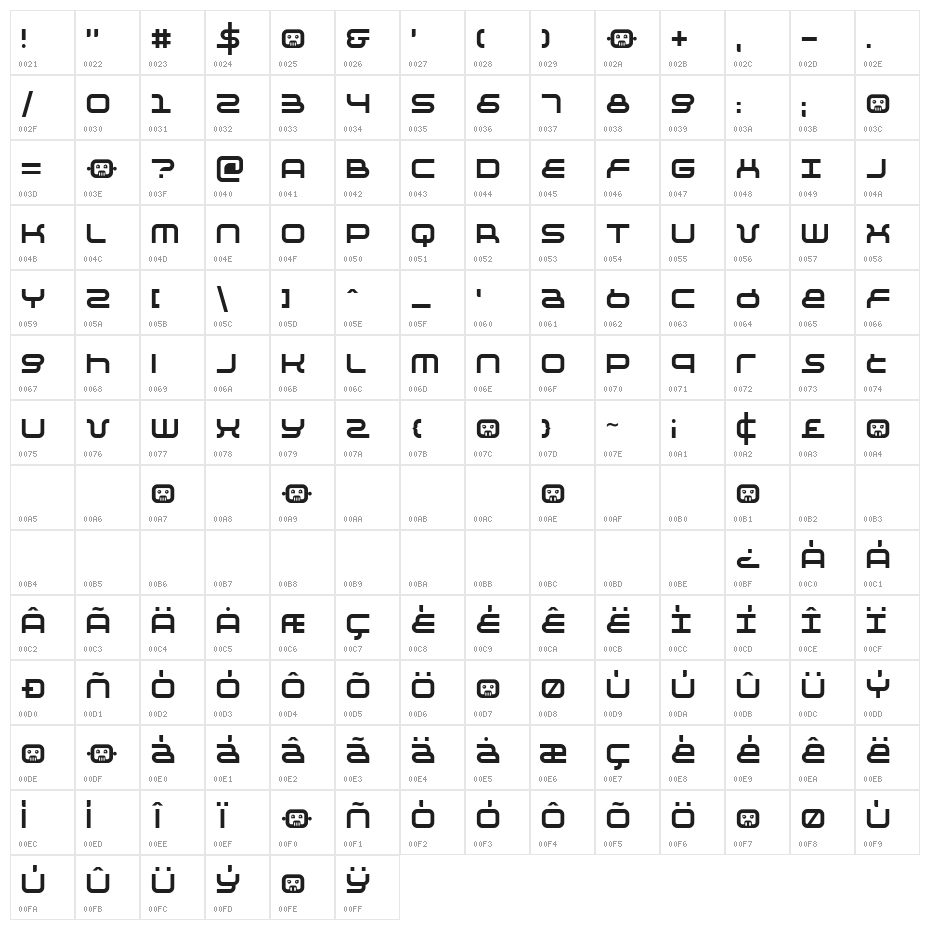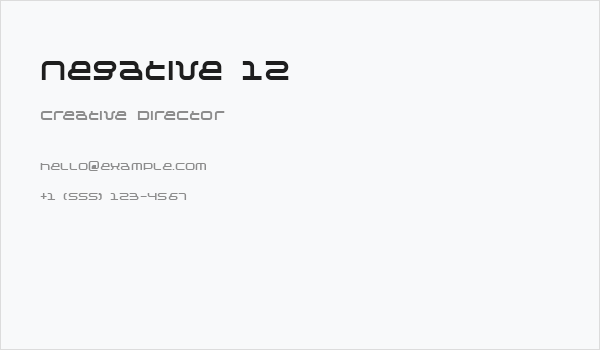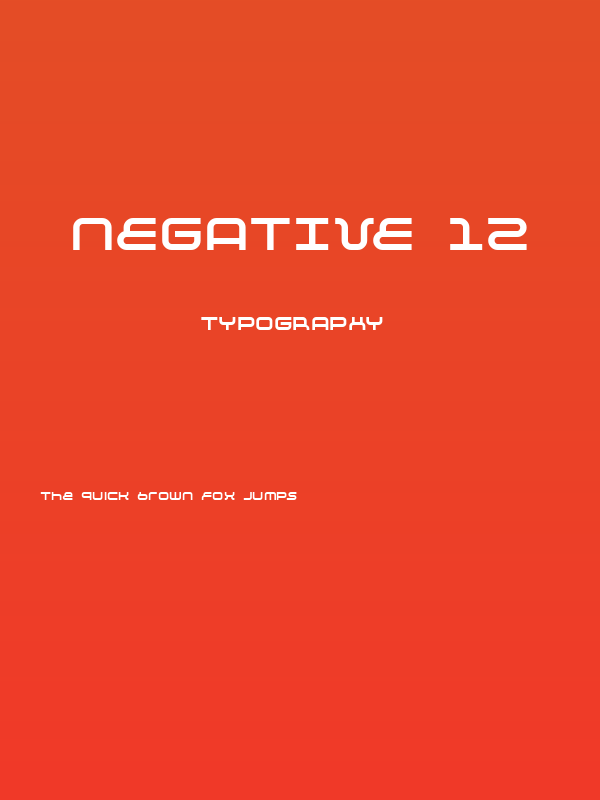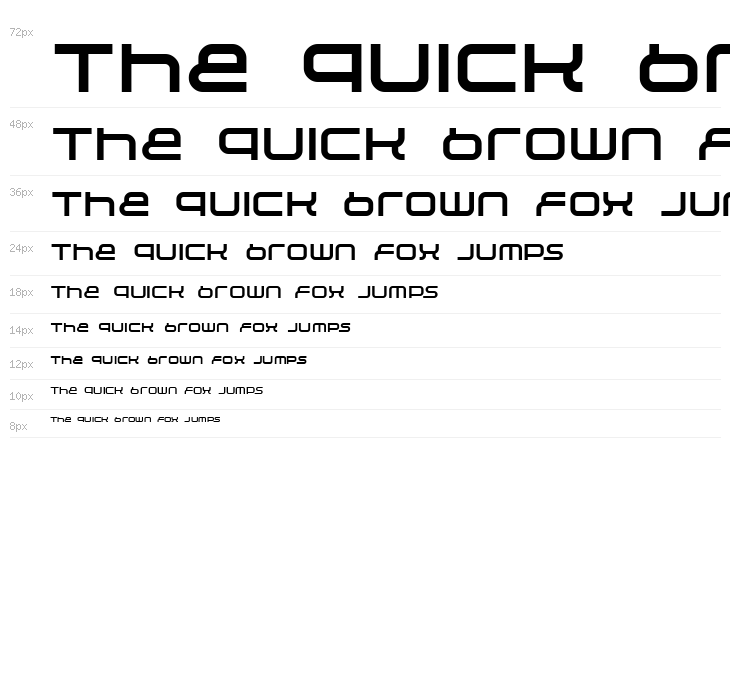
Negative 12 Font
| 全体的なスタイル | Futuristic |
| 用途 | Logos, Digital interfaces, Branding |
| おすすめプロジェクト | Ideal for technology branding, sci-fi themed designs, modern logos, and digital interfaces. |